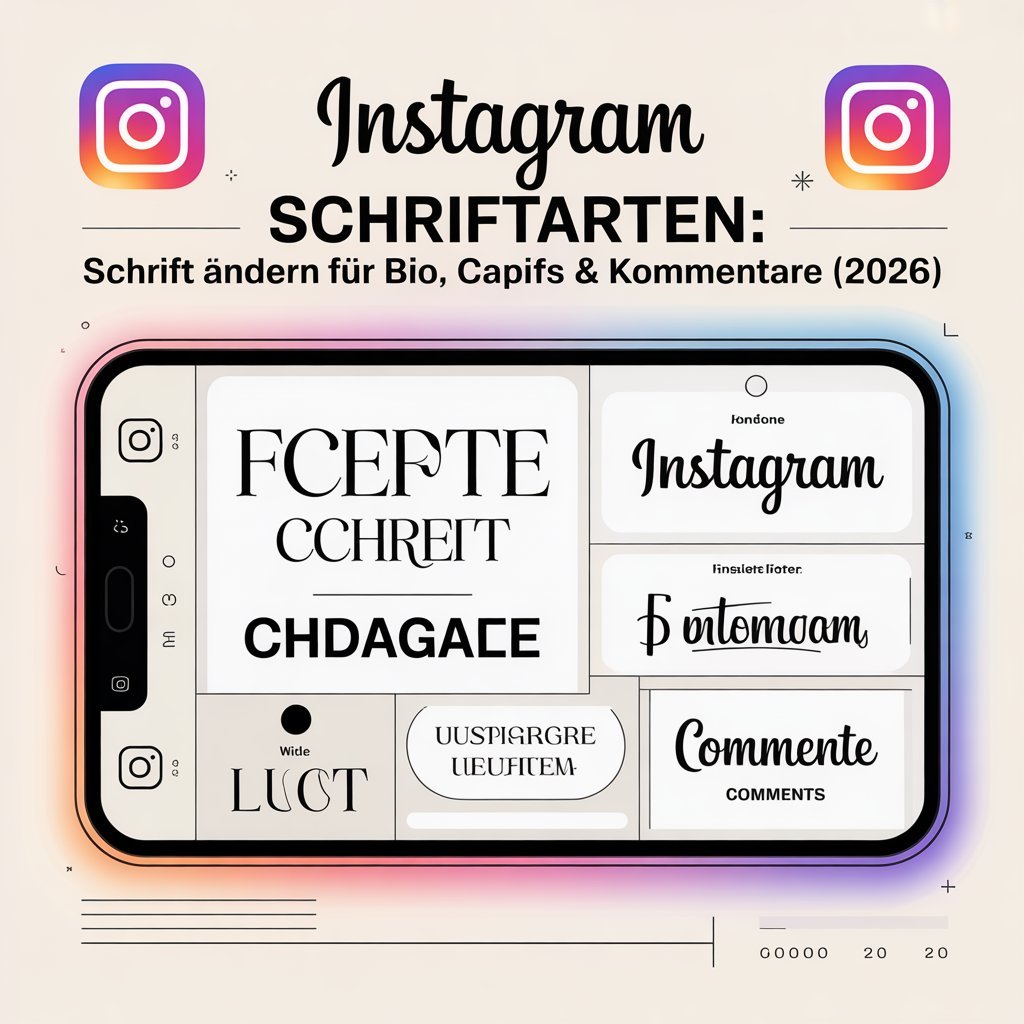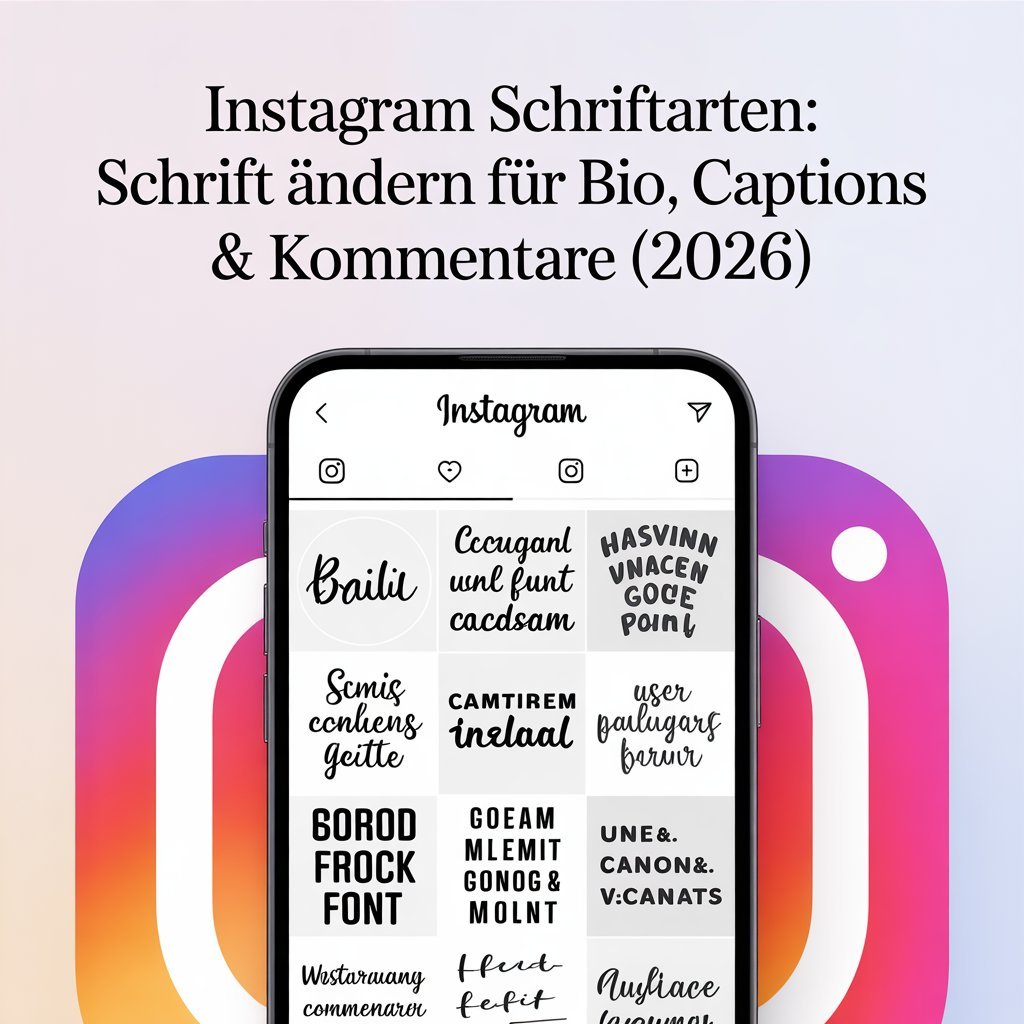
Instagram Schriftarten Generator – Schrift für Bio, Name & Posts kopieren
2022 hab ich mein erstes Business-Konto auf Instagram angelegt. Bio fertig, Foto hochgeladen, Profil live. Drei Wochen später: 47 Aufrufe, null Anfragen. Mein Bekannter mit dem gleichen Angebot hatte 600 Aufrufe – einziger sichtbarer Unterschied war sein Profilname in Fettschrift.
Das klingt banal, ist aber kein Zufall. Studien zum Blickverhalten auf mobilen Feeds zeigen: Profile mit visuell abhebenden Elementen bekommen 30–40% mehr Klicks bei gleichem Inhalt. Schrift ist das günstigste Abhebemittel, das du hast.
Instagram selbst gibt dir exakt eine Schriftart: Proxima Nova. Kein Fettdruck in der Bio, keine Kursivschrift im Namen, keine Schnörkelschrift irgendwo. Was du auf anderen Profilen siehst, sind keine echten Schriften – das sind Unicode-Sonderzeichen, die wie Buchstaben aussehen.
Dieser Generator wandelt deinen Text automatisch in über 50 Unicode-Stile um. Kein Download, kein Konto, kein Abo. Du tippst rein, wählst einen Stil, kopierst – fertig. Ich zeige dir außerdem, welche Stile wirklich funktionieren und welche Fehler dein Profil schlechter aussehen lassen.
Warum Instagram keine Schriftarten erlaubt – und wie Unicode das löst
Instagram rendert alle Profilfelder im gleichen Textformat. Das System kennt keine Font-Tags, keine Formatierungsbefehle, keine benutzerdefinierten Schriften. Was du eintippst, wird 1:1 in Proxima Nova dargestellt.
Unicode ändert das Spiel. Der Standard definiert über 140.000 Zeichen – darunter mathematische Symbole, die optisch wie Buchstaben aussehen, aber technisch andere Zeichen sind. Ein 𝗮 (Mathematical Bold Small A, U+1D41A) ist nicht dasselbe wie ein normales a. Instagram zeigt beide an, weil der Unicode-Standard unterstützt wird.
Ein Instagram Schrift Generator tauscht jeden Buchstaben deines Textes automatisch gegen das passende Unicode-Äquivalent aus. Das geht in Millisekunden und funktioniert in Bio, Profilname und Captions.
Einschränkung: In Instagram Stories und Reels gibt es native Schriftoptionen direkt in der App. Dort brauchst du keinen externen Generator – dazu weiter unten mehr.
Die 10 beliebtesten Instagram Schriftarten – Übersicht und Empfehlung
Nicht jede Unicode-Schrift sieht auf jedem Gerät gleich aus. Diese Stile funktionieren auf iOS und Android zuverlässig:
Mein Fazit nach zwei Jahren: Fettschrift und Klein-Caps sind die verlässlichsten Stile für Business-Profile. Schnörkelschrift sieht im Screenshot toll aus, kostet aber bei kleiner Display-Darstellung Lesbarkeit – und Lesbarkeit kostet Follower.
Instagram Schrift ändern – Schritt für Schritt
Instagram hat keine eingebaute Option, die Schriftart zu wechseln. Der Weg geht immer über einen externen Generator. Hier ist der genaue Ablauf für jedes Profilfeld:
Schrift in der Bio ändern
Wichtig: Manche Unicode-Zeichen zählen im Instagram-Limit als zwei Zeichen. Wenn der Text zu lang wird, wähle einen einfacheren Stil oder kürze deinen Text.
Schrift im Profilnamen ändern
Gleicher Ablauf, aber: Du hast nur 30 Zeichen. Und Instagram erlaubt Namensänderungen maximal zweimal in 14 Tagen. Deshalb vorher testen, nicht direkt live speichern.
Für Namen funktionieren kurze, klare Stile am besten. Fettschrift oder Klein-Caps – nicht Schnörkel oder Fraktur. Je kleiner der Name auf dem Profil dargestellt wird, desto wichtiger ist Lesbarkeit über Optik.
Schrift in Captions und Kommentaren
Hier gibt es kein Zeichenlimit-Problem. Trotzdem: Schrift sparsam einsetzen. Ein oder zwei fettgedruckte Wörter lenken die Aufmerksamkeit gezielt. Wer alles hervorhebt, hebt nichts hervor.
Captions komplett in Unicode-Schrift zu schreiben ist außerdem kontraproduktiv fürs Algorithmus-Ranking – der Instagram-Algorithmus erkennt Unicode-Zeichen nicht als normalen Text.
Instagram Bio Copy Paste – Der schnellste Weg zur besseren Bio
Über 33.000 Deutsche suchen monatlich nach „instagram bio copy paste“. Der Wunsch ist klar: Einfach kopieren, einfügen, fertig. Genau das macht dieser Generator.
Zurück zu meinem Bekannten aus dem Anfang: Sein Geheimnis war kein besonderes Content-Format, kein teures Shooting, kein Algorithmus-Hack. Er hat seinen Profilnamen in Fettschrift geschrieben – fertig. Drei Minuten Aufwand.
Du weißt jetzt, wie der Instagram Schrift Generator funktioniert, welche Stile wo sinnvoll sind, wie du die Bio strukturierst, und welche Fehler dein Profil schlechter aussehen lassen. Das Tool oben macht den technischen Teil in Sekunden.